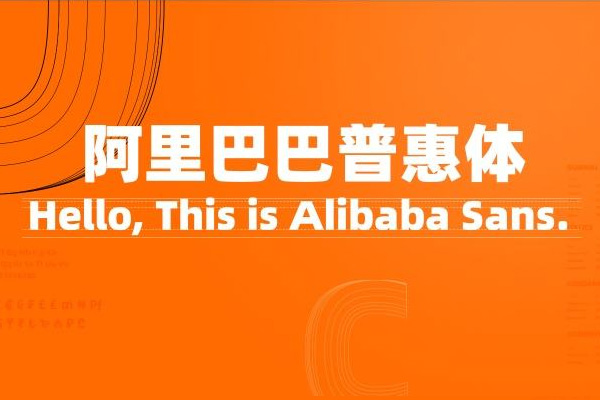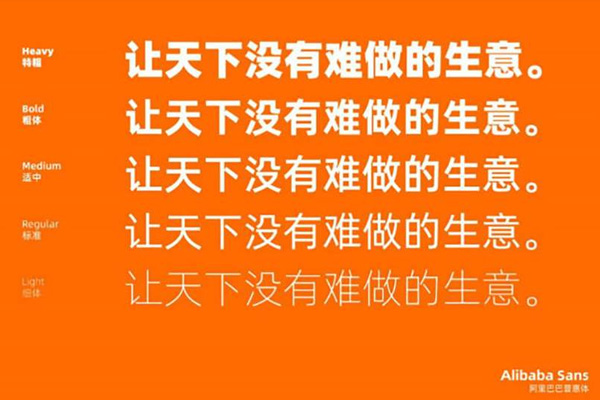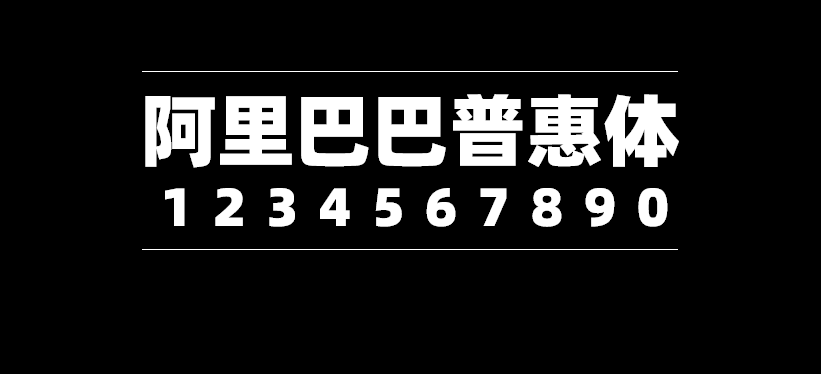
阿里巴巴普惠体
阿里巴巴新发布的免费字体,首开企业发布免费字体先河,赚足了口碑,当然也少不了争议,不过作为一款免费可商用字体,是非常不错的了,包含5种不同字重,字符也比较全,字形上比较接近微软雅黑和思源黑体。 不过下载稍微繁琐一些,官方明确限定字体必须到官网下载,禁止转载上传,所以请点击下方“相关链接”到官方下载。